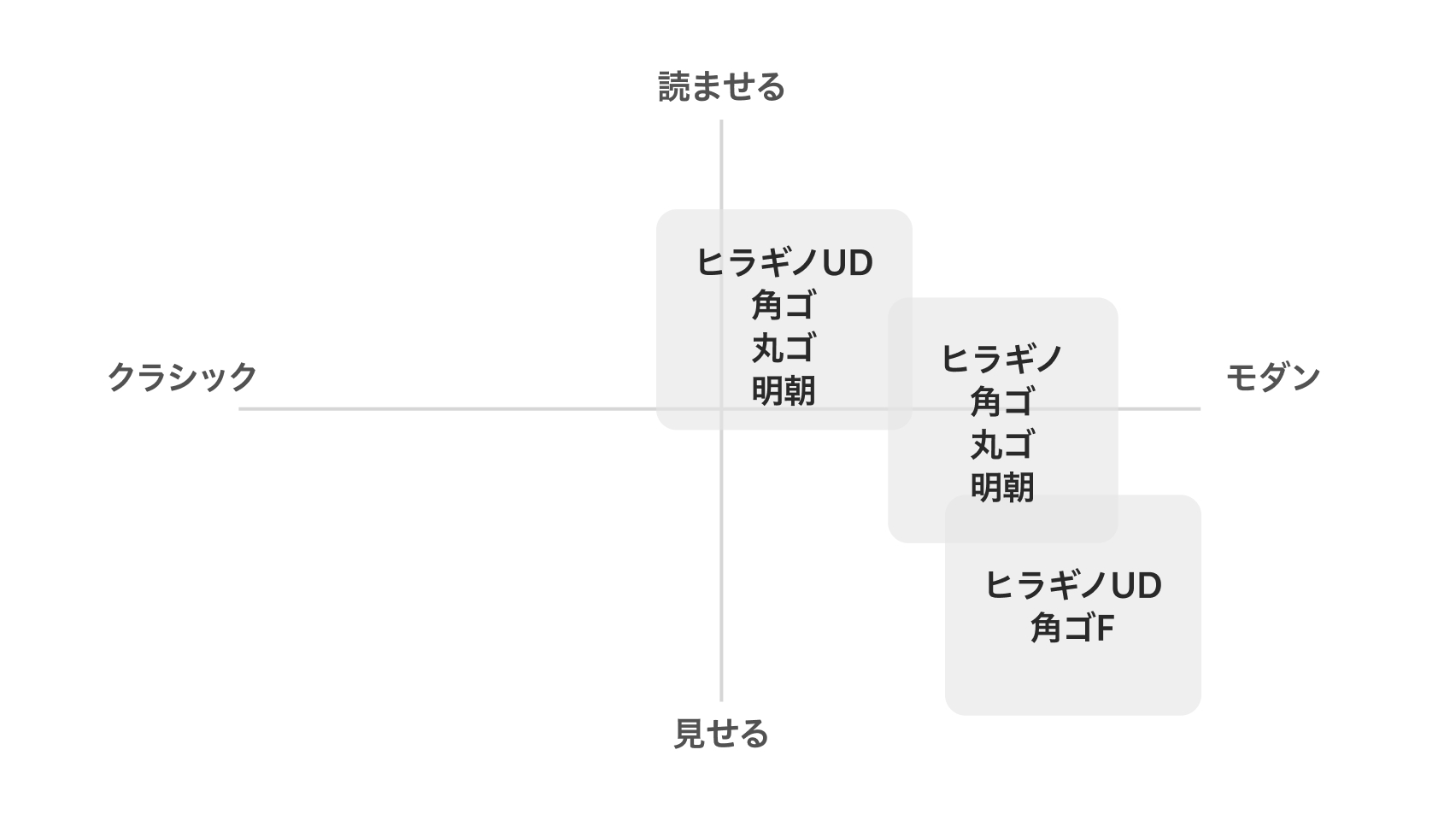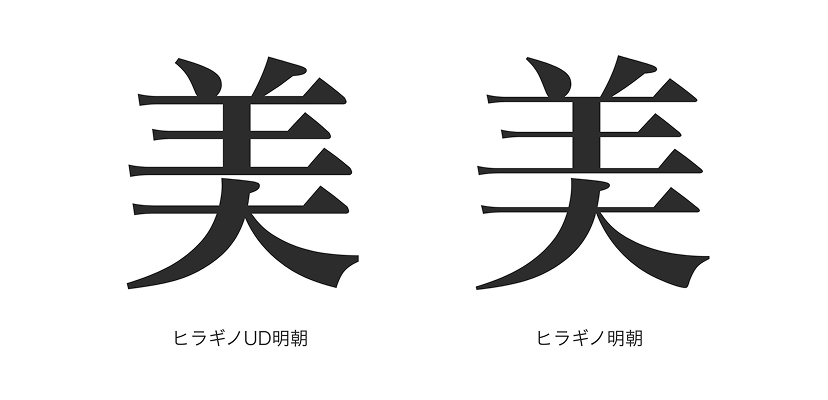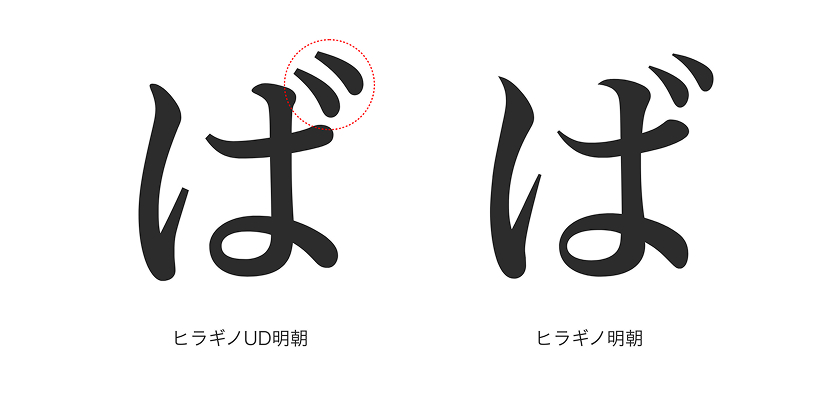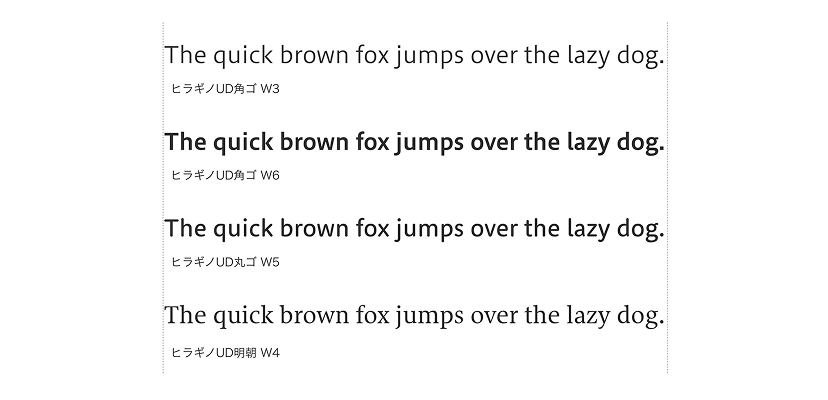
ヒラギノUD明朝
ひらぎのゆーでぃーみんちょう
Hiragino UD Serif
ヒラギノUD明朝は、ヒラギノ明朝の基本デザインを受け継ぐユニバーサルデザインのフォントです。長い文章の読みやすさを求めて、字面をやや小さめにまとめ、仮名には長く読んでも疲れないやわらかな骨格を採用。画のストロークをシンプルにしながら、大きさの異なる漢字・仮名・欧文が文章に自然な抑揚・リズムを生み出し、文字に求められる美しいデザイン性と長い文章も心地よく読み続けられる可読性を提供します。小さい文字で使用すると横線やハライの先端が細く飛んでしまうという明朝体特有の事象に配慮して細部を最適化し、小さな文字での印刷や、組込みやディスプレイなどでも使いやすい明朝体をめざしました。
もちろん誤読をさける濁点・半濁点の強調の他、数字と欧文には判読性を高めるUDオリジナルデザインを採用。さらにはヒラギノUD全書体で採用している共通文字幅により、書体やウエイトを変えても同じ行長を維持できます。文字原稿の変更やデザインの改訂などの際、余分な工程を増やすことなく容易に対応していただけるなど、UDシリーズならではの優位点はしっかりと堅持しています。
雑誌本文、Webデザイン、サインデザイン、テレビテロップなど幅広い用途に対応し、印刷でもディスプレイ表示でも、縦組みでも横組みでも美しい組版を実現します。
ヒラギノUD角ゴ・ヒラギノUD明朝・ヒラギノUD丸ゴは、中庸で「長く/楽に/読ませる」ことを重視しています。一方、ヒラギノUD角ゴFは、ヒラギノの現代的なデザインの印象を引き継ぎ、「くっきりと/見せる」ことを重視しています。
長く読んでも疲れにくい、すっきり柔らかな骨格を採用。ひらがな、カタカナのストロークの先端部分にはやや丸みを持たせ、落ち着いた印象を与えます。
ヒラギノUDフォントの仮名は誤読につながりやすい濁点・半濁点を大きめに修正しています。濁点は点と点の位置を広げ、より明るく読みや取りやすくなっています。
ヒラギノUDフォントの従属欧文は「1」や「7」、「C」や「O」など読み間違えやすい文字の誤読防止に配慮しています。欧文書体単体としても美しく、和欧混植の文章もスムーズに読み進めることができます。
通常は、スタイル(セット・ウエイト)ごとに異なる文字幅とプロポーショナルピッチをヒラギノUDフォント内ですべて共通化。スタイルや太さを変えても組版が崩れません。